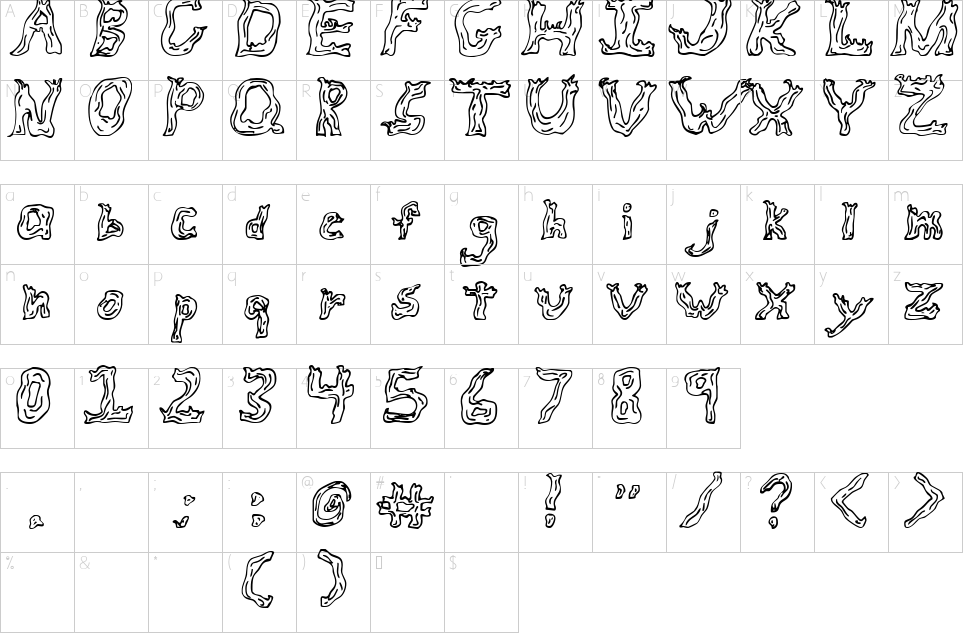
Descubra a fonte ‘Fire Wood’ grátis em seu site de fontes para Windows e Mac. Desenvolvida pelo designer Bionic Type, a ‘Fire Wood’ tem uma aparência natural e elegante, perfeita para criar um design interessante e envolvente. Esta fonte tem sido descarregada mais de 7.300 vezes, o que prova seu valor e qualidade. Baixe a sua e experimente a diferença em seus projetos. Aproveite esta fonte para adicionar um toque único e sofisticado a seus designs.